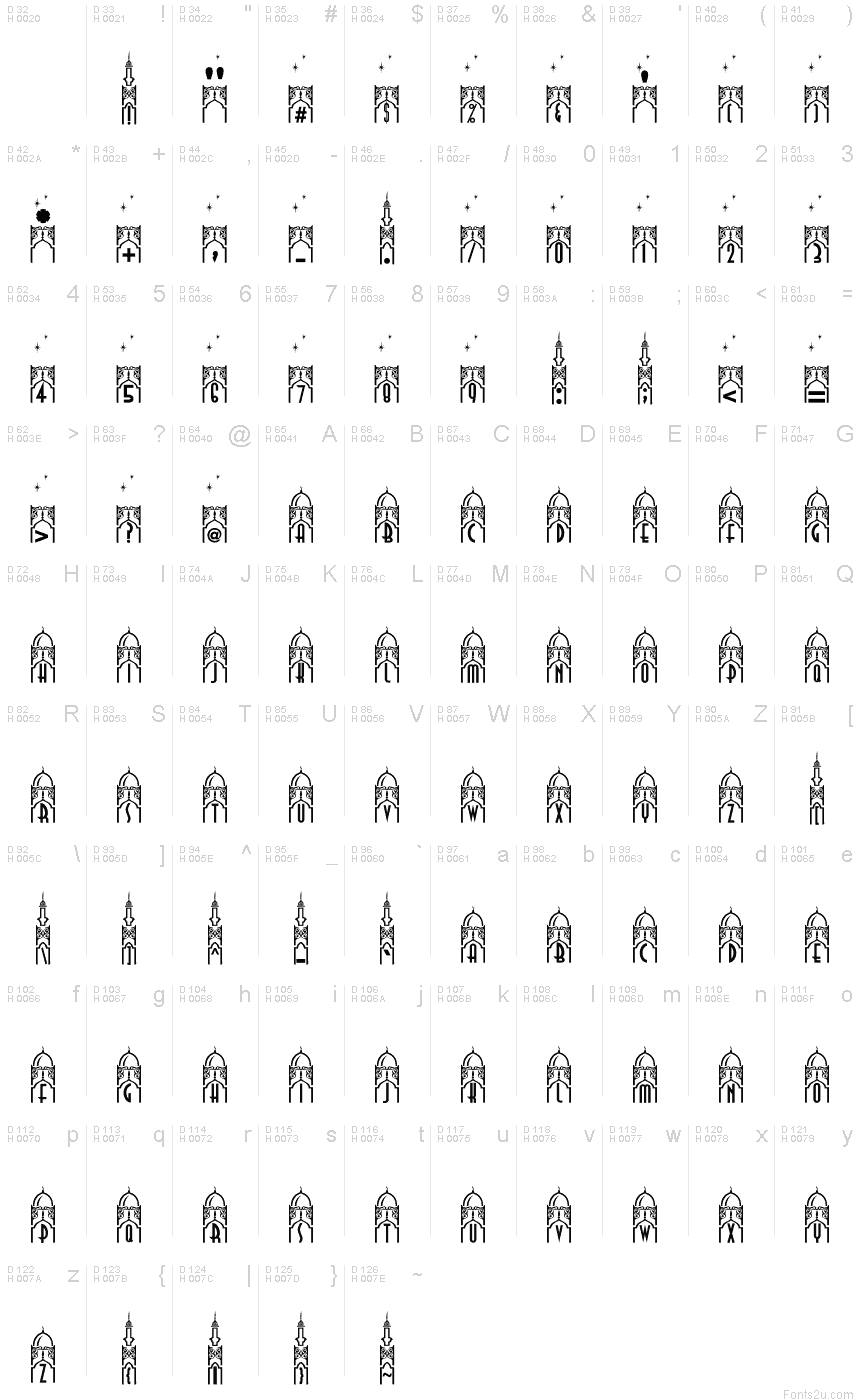
UKIJ Imaret od Uyghur Computer Science Association to bezpłatny krój ozdobny inspirowany osmańskimi łukami, kopułami i misternymi zdobieniami wnętrz. Powtarzalna, przypominająca meczet struktura nadaje mu ceremonialny, architektoniczny charakter, podczas gdy odważne pionowe linie sprawiają, że font zachowuje wyrazisty, plakatowy styl, zamiast wyglądać zbyt delikatnie.
Ten darmowy font świetnie sprawdzi się w brandingu festiwali kulturalnych, okładkach książek, plakatach imprezowych, menu restauracji oraz opakowaniach, które wymagają akcentów architektury islamskiej bez użycia ilustracji. Bardzo dobrze sprawdza się również w krótkich nagłówkach czy monogramach, gdzie wysoki łuk sprawia, że nawet pojedynczy znak wygląda jak brama lub fasada budynku.